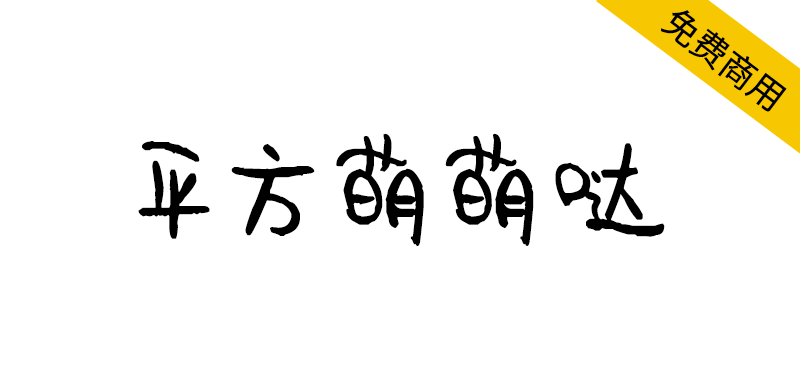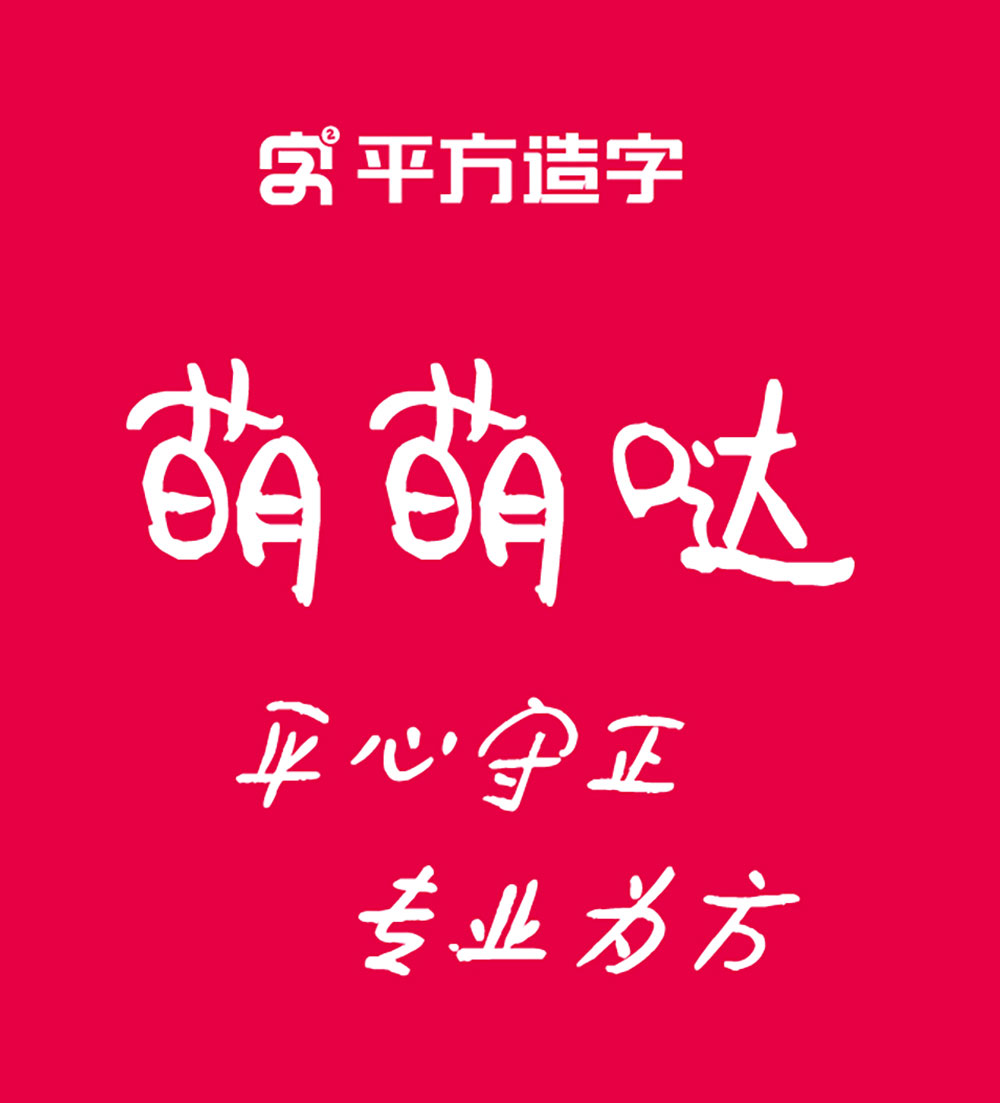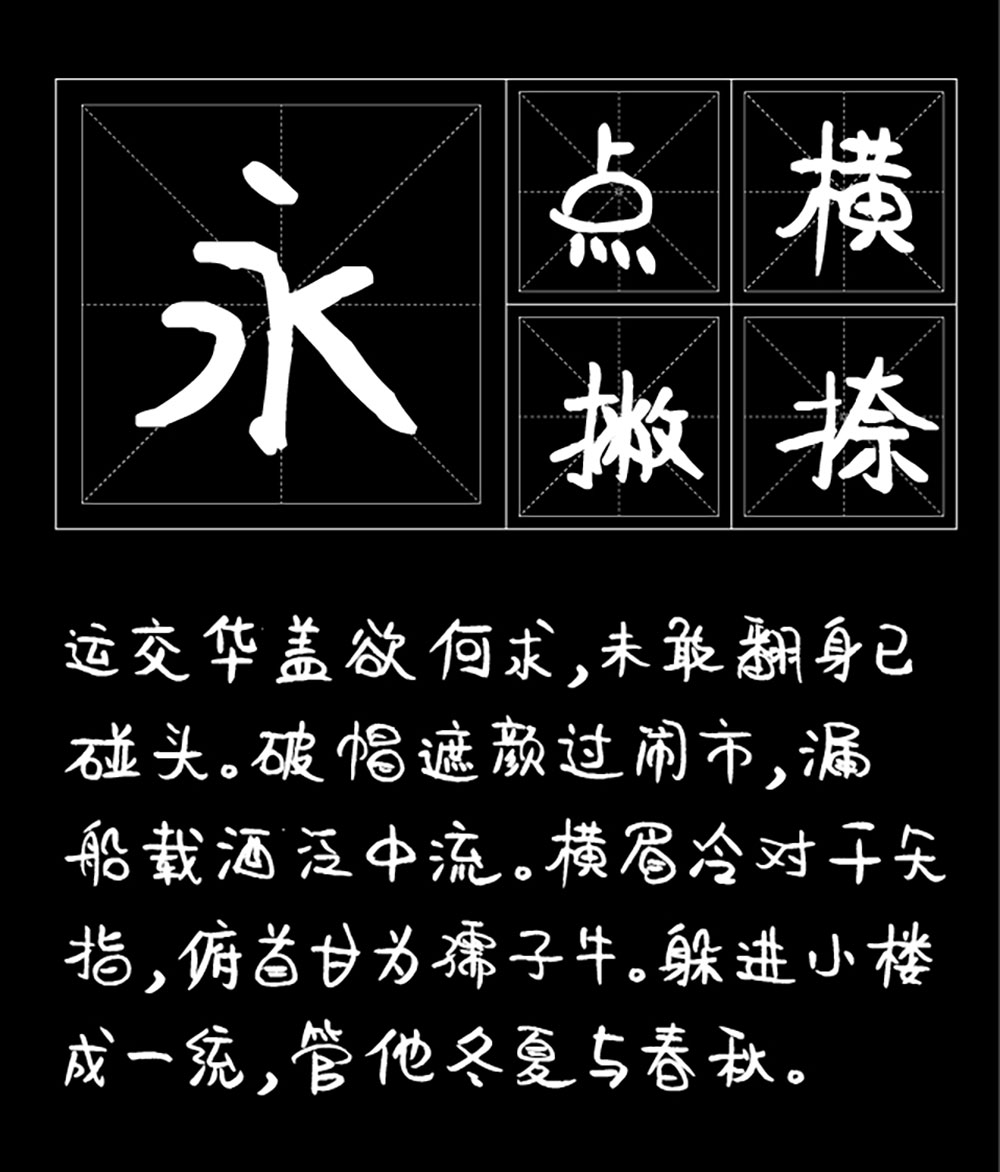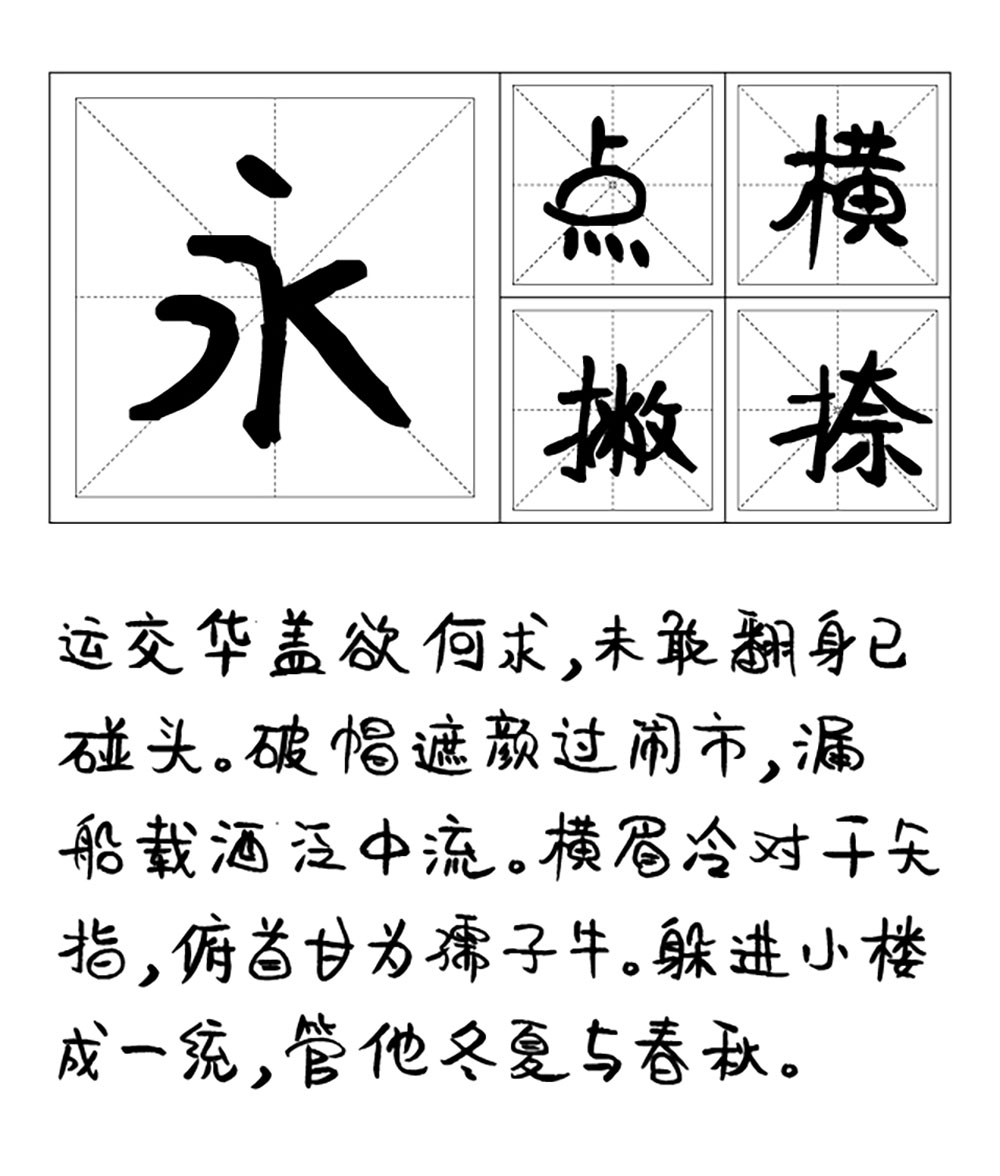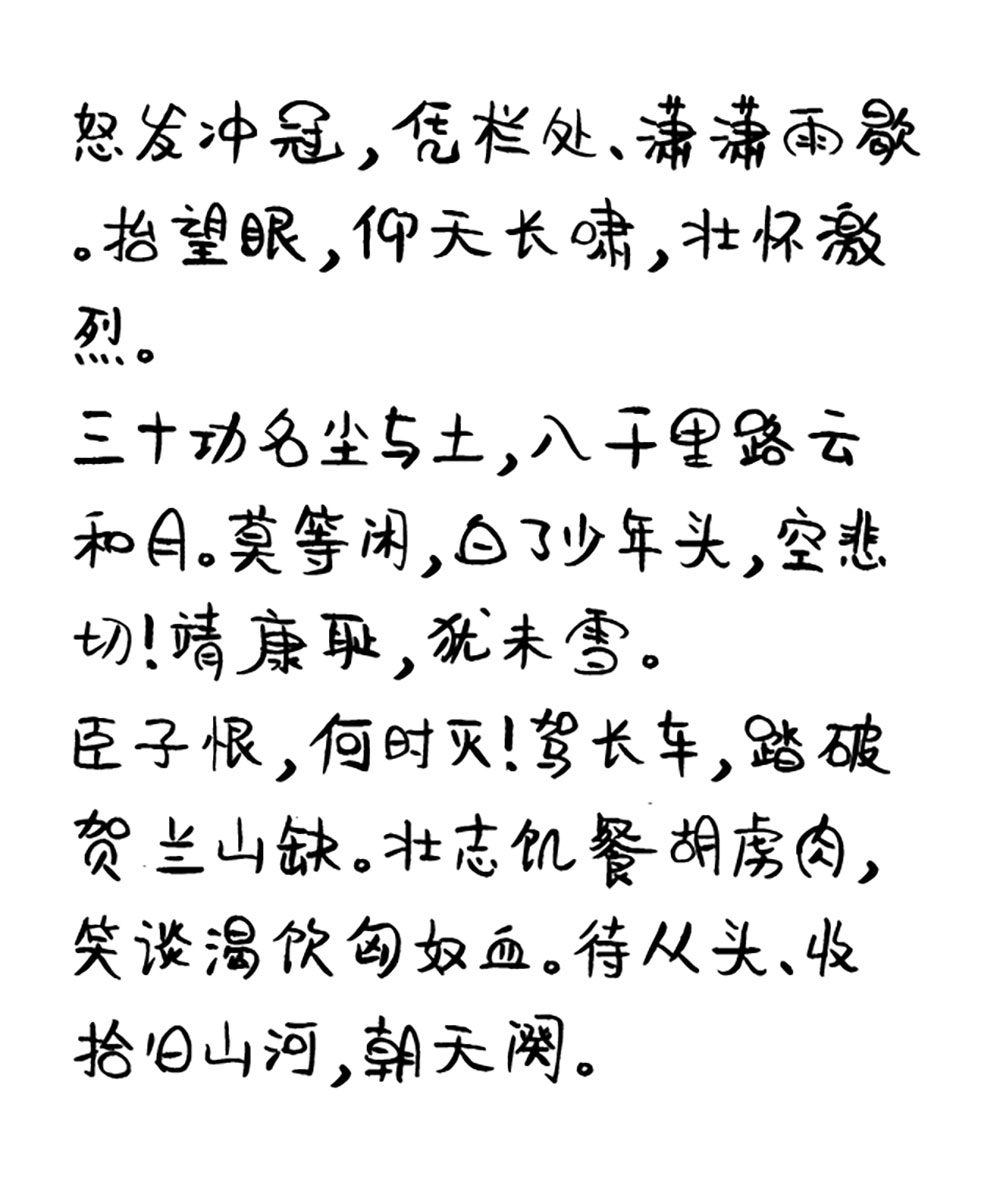
【平方萌萌哒】一款可爱活泼的创意手写体字体
想让你的文字会“跳舞”吗?“平方萌萌哒”字体来了!它笔画灵动,活泼俏皮,自带萌系滤镜,能瞬间点亮你的设计。更惊喜的是,这款宝藏字体支持个人与企业免费商用,无论是海报、自媒体还是电商,都能放心使用,快来为你的创意增添一抹童趣吧!
【平方萌萌哒】一款可爱活泼的创意手写体字体
平方萌萌哒是一款充满童趣的手写风格字体,其横笔画呈现自然流畅的微弧曲线,线条粗细恰到好处。字体整体结构活泼灵动,洋溢着俏皮可爱的气息,特别适合用于各类萌系主题的文案排版与设计场景。
平方萌萌哒为创意手写体,字体如其名称可爱活泼,深受广大学生党追捧,适用于各种场合,为中文简体字库。字体采用OpenType格式,基于中华人民共和国GB2312-80字符集标准,共收容字数6763汉字,常用标点符号123个,共计字符6886个。